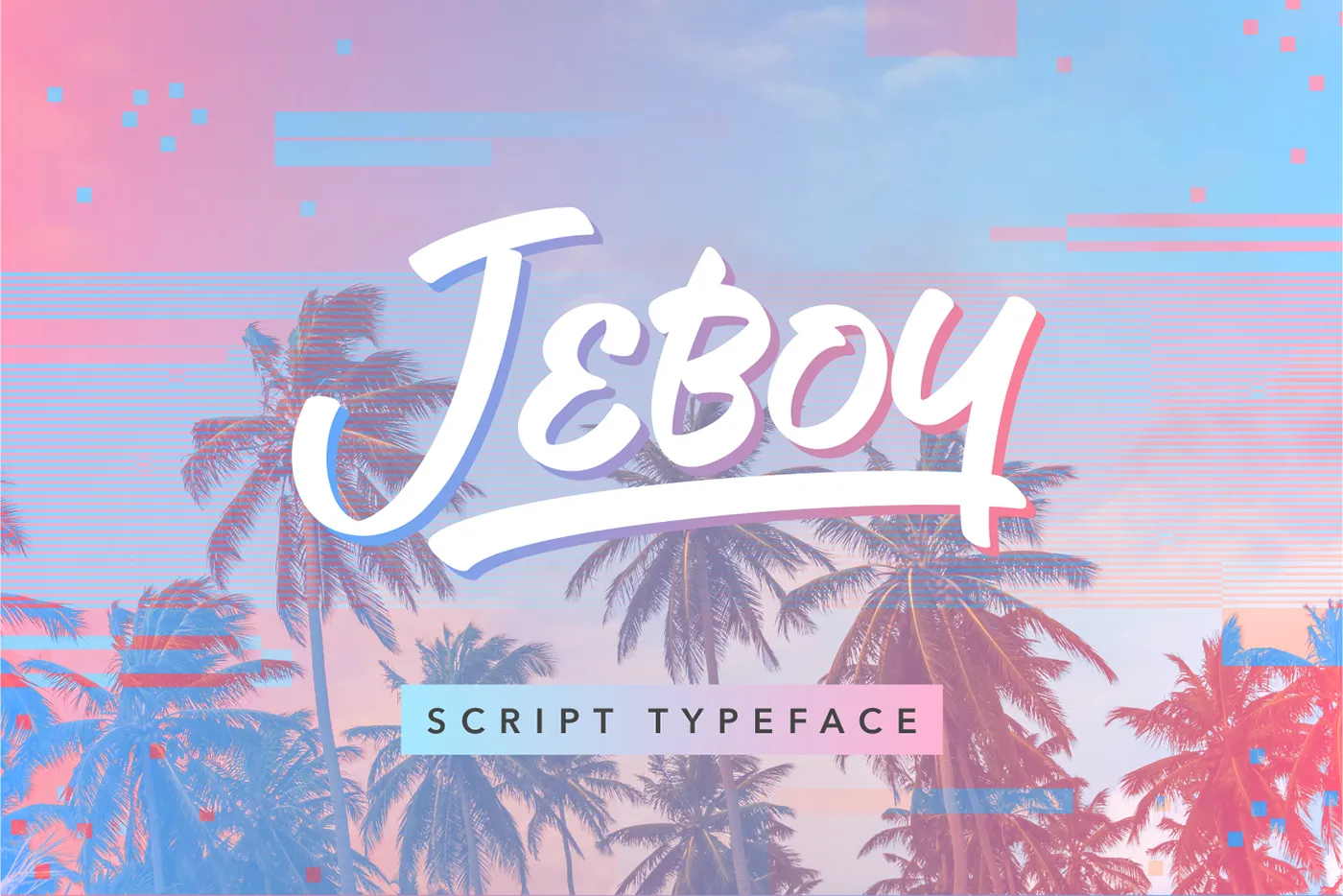
Jeboy Typeface
A fonte Jeboy Typeface é uma elegante seleção de linhas brush, criada pelo designer Hamilton para aqueles que valorizam a arte natural na tipografia. Essa fonte oferece um toque cuidadosamente elaborado, com traços fluidos e delicadamente arranhados que permitem criar texturas imersivas e vibrantes em qualquer projeto gráfico. Ideal para designers que buscam uma solução única e expressiva para seus projetos, a Jeboy Typeface é perfeita para aplicar em logotipos de marcas, criações de ambientes digitais, ou até mesmo para adicionar um toque autêntico ao design editorial. Com seu estilo único, essa fonte brush permite que você transborde emoção e personalidade em cada projeto, tornando-a uma escolha excepcional para designers buscando dar vida aos seus projetos visuais.